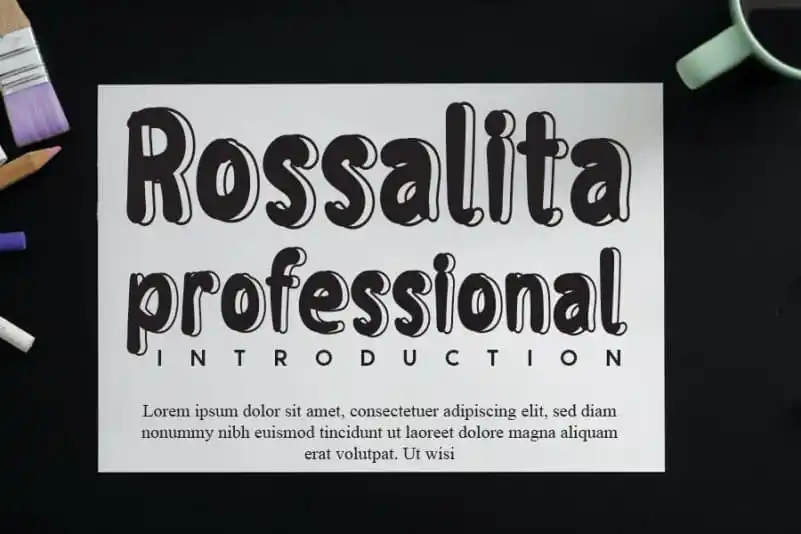
Rossalita Display Font é uma elegante escolha para quem busca uma mistura moderna de confiança e casualidade no seu design visual. Desenhada com cuidado por mão humana, esta fonte display se destaca pela sua personalidade descontraída que faz dela uma opção ideal tanto para o estilo de escrita quanto para as aplicações visuais mais impactantes. Seu aspecto levemente despojado confere a ela um charme natural e elegante, tornando-a perfeitamente adaptável a diversos ambientes, desde backgrounds bem agitados até headlines de destaque isoladas. Perfeito tanto para uma apresentação técnica quanto para gráficos visuais criativos, esta fonte oferece uma abordagem versátil que se adequa a qualquer necessidade visual. O resultado é um elemento gráfico poderoso e elegante, capaz de destacar seu trabalho em qualquer contexto. Rossalita Display Font é ideal para designers buscando combinar força com charme no seu projeto.